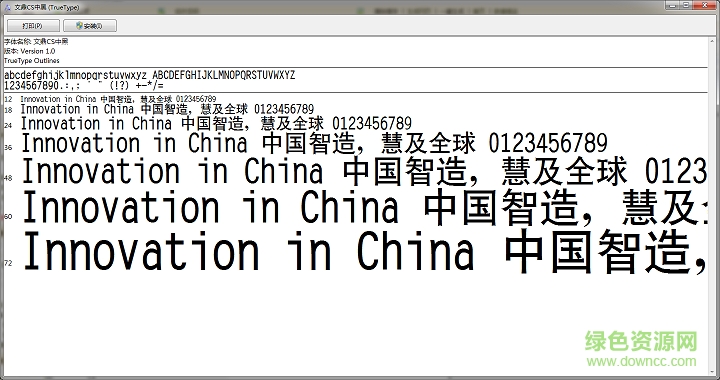
heiticseg-medium-gb是什么字體?heiticsegmediumgb字體又叫文鼎CS中黑字體,字體結(jié)構(gòu)規(guī)范,簡潔無裝飾,多用于印刷、文本標(biāo)題等領(lǐng)域,也可用作正式場合的書面報告字體!
黑體字是現(xiàn)代漢字體系中最重要的字體之一。尤其是隨著20 世紀末電腦和互聯(lián)網(wǎng)的普及,黑體字的價值得到了進一步體現(xiàn),它簡潔的筆畫特征與屏顯介質(zhì)特性相符,從而成為了當(dāng)今各種屏幕媒介中最有發(fā)展前景的無襯線字體。